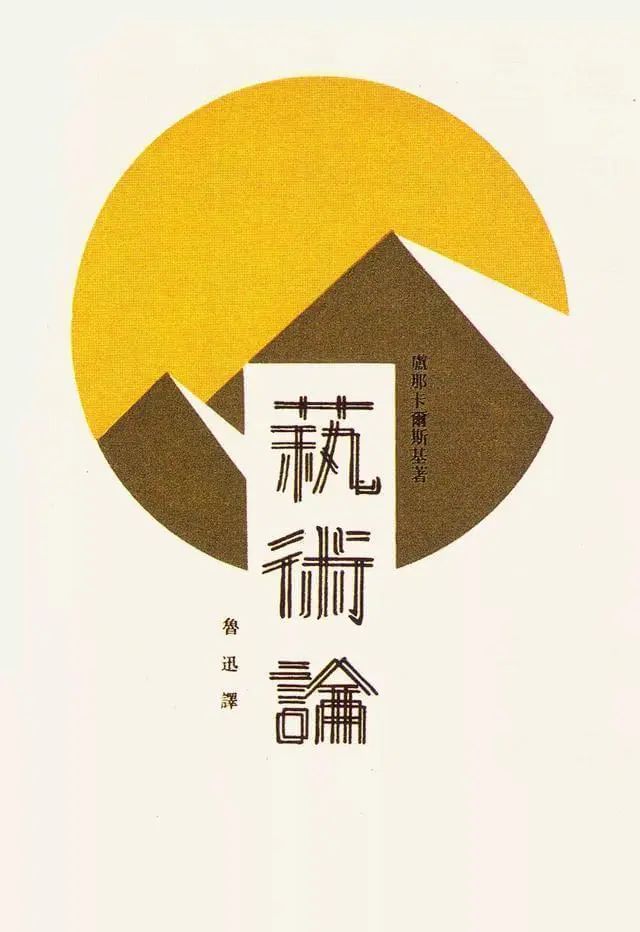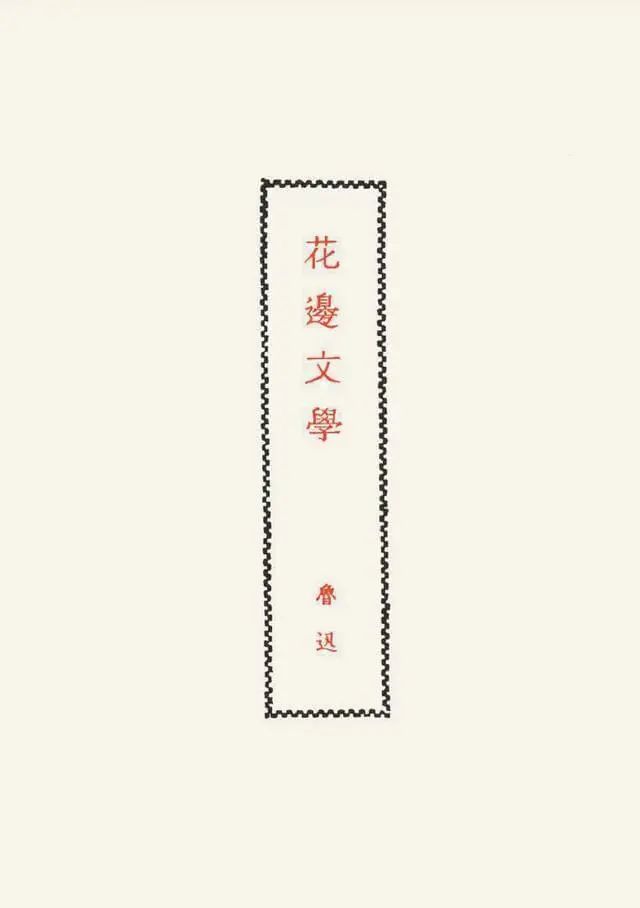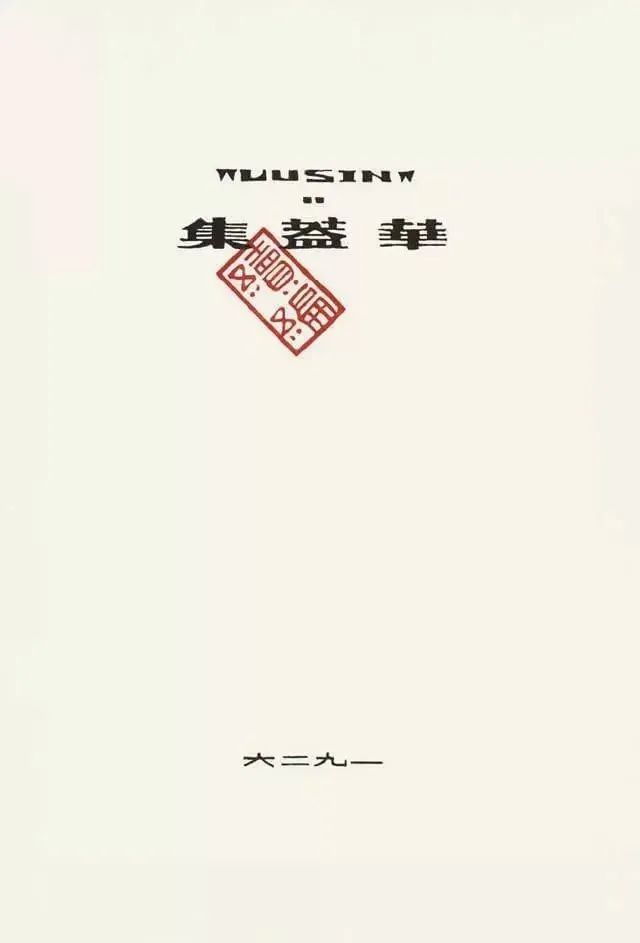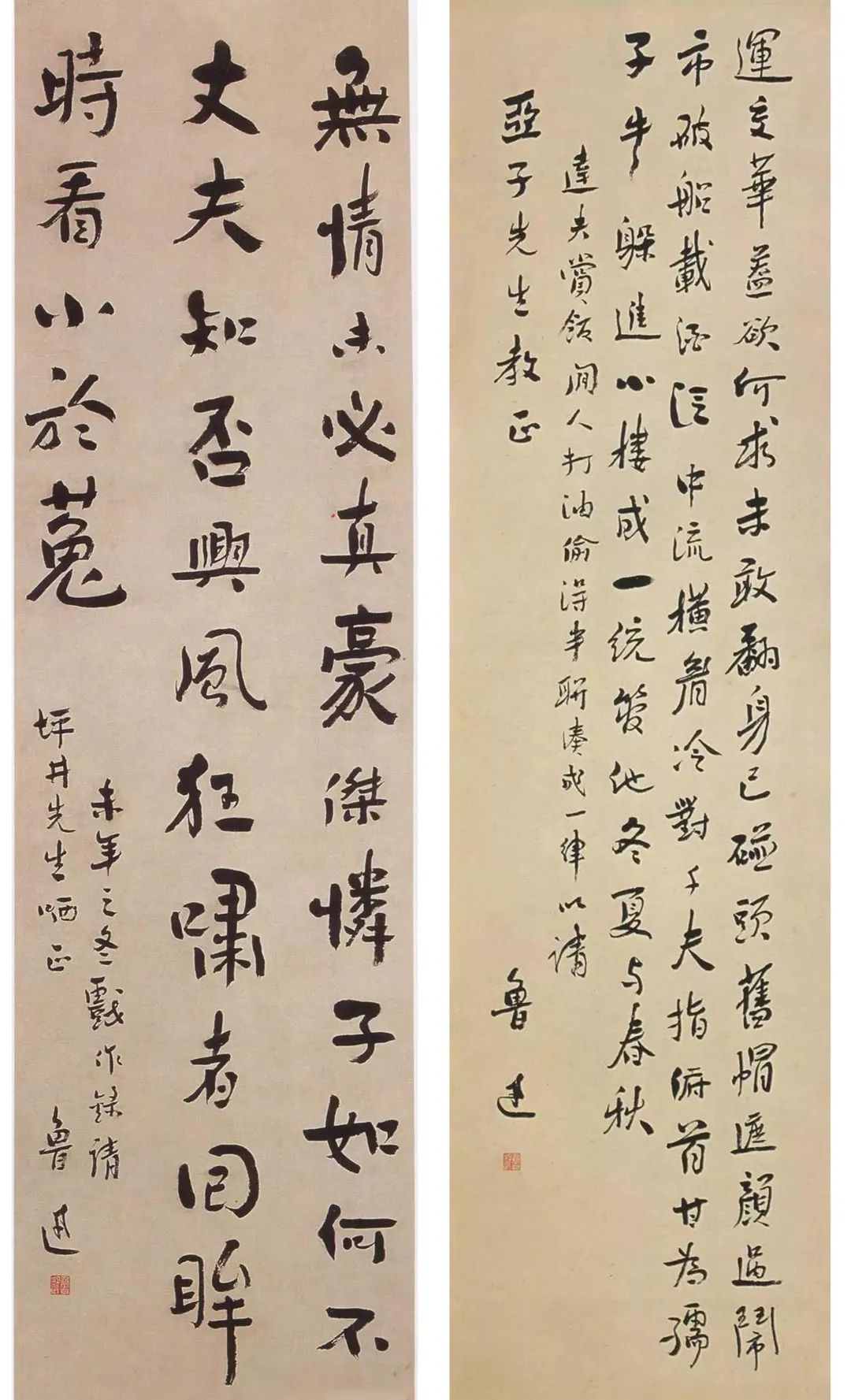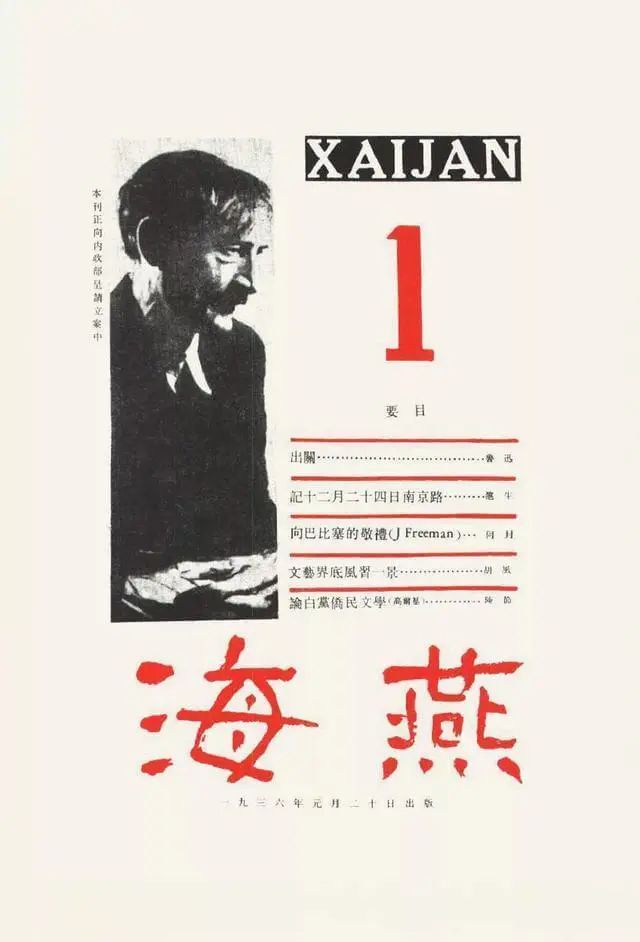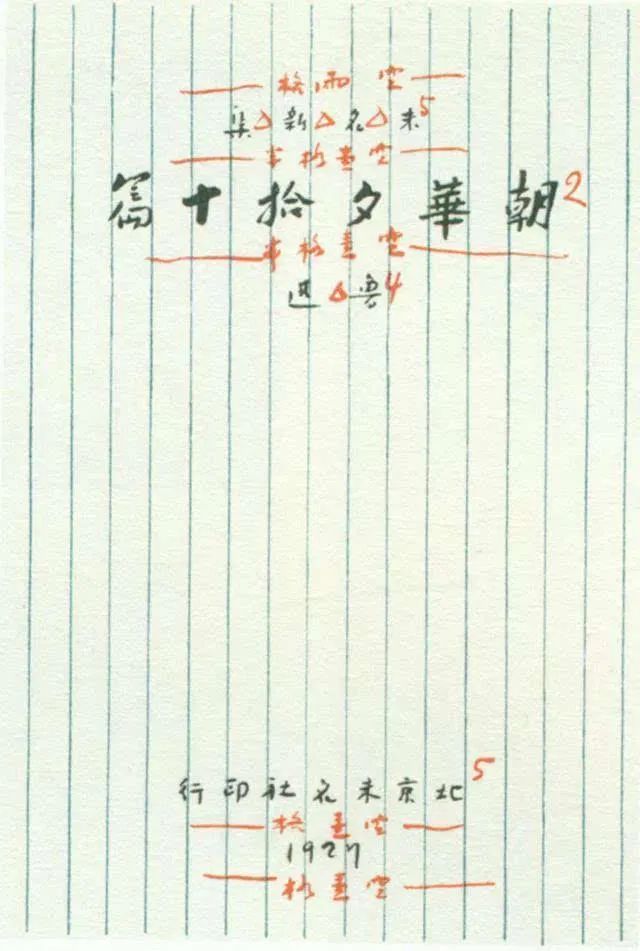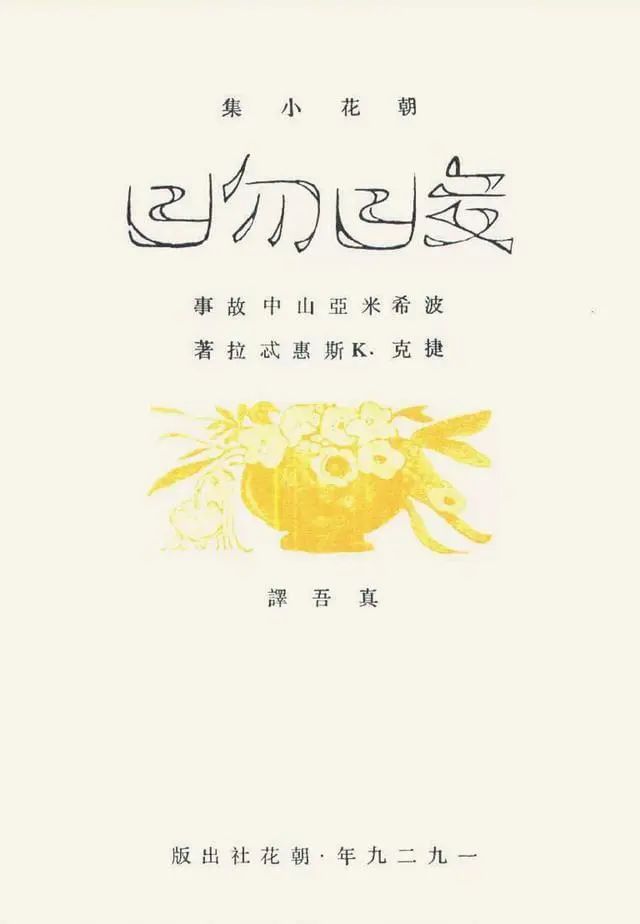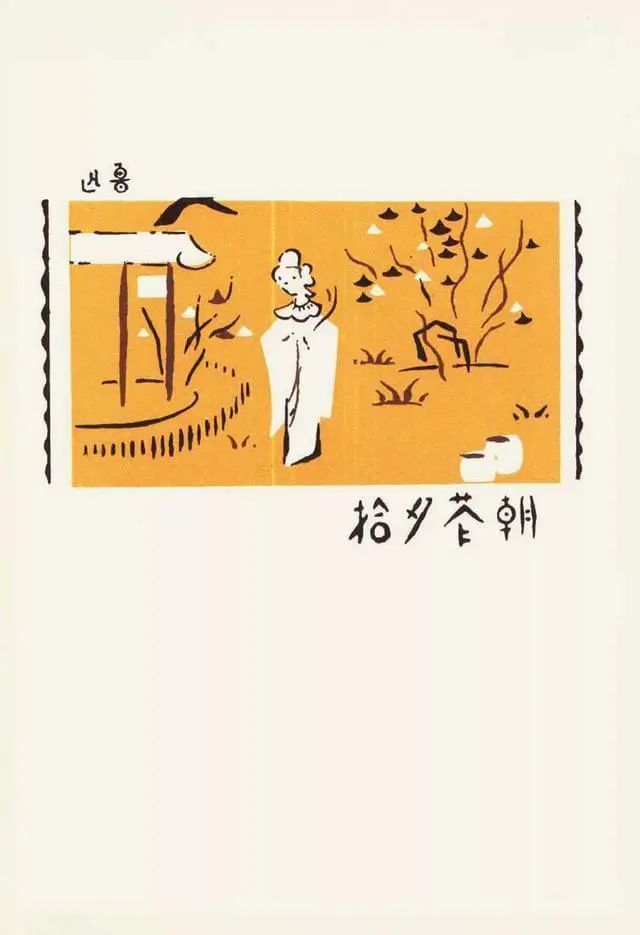
提到鲁迅先生,大家印象最深的是什么?
有的人会说是他的那些金句,有的人会觉得是他那两撇胡子,而我印象最深的就是中学课本里,他那些文学作品,和文章后面的背诵全文,对于鲁迅先生,我们每个人都知道,他是伟大的文学家,思想家,殊不知,鲁迅先生还有不为人知的一面,创作一本书,主笔是他,插画是他,封面设计是他,装帧也是他,样样精通,所以如果只是说他是文学家,那这个定位稍微有些片面了,今天我们就来聊一聊鲁迅先生的那些设计作品。
鲁迅1881年出生在浙江绍兴,爷爷爸爸都是文人,父亲是秀才,但是因为种种原因入狱,出狱之后终日饮酒,导致患病,当时鲁迅也只是十多岁的少年,在三味书屋学习,但是作为长子,他知道自己肩负的责任,那之后他每天都要跑当铺药铺去给父亲抓药,据鲁迅先生后来回忆来看,当时他在当铺受的侮蔑是让他刻骨铭心的,父亲去世之后,他便离开了故乡。
鲁迅先生念过的<三味书屋>他说:“书没读成,画的成绩却不少了,最成片段的是《荡寇志》和《西游记》的绣像,都有一大本。”
在《阿长与山海经》和《从百草园到三味书屋》中都有描述过鲁迅先生儿时非常喜欢带有绘图的书籍,就是在这里,鲁迅先生埋下了艺术的种子。
之后他去了南京江南水师学堂求学,以优异的成绩获得公费赴日本学习的机会,在日本,他读了很多关于美学和文学方面的相关书籍,但他一直抱有学医的梦想,希望学成归来之后能救治像他父亲一样的病人,遇到战争也可以当军医,但是后来因为看了关于同胞被屠杀的照片,这成为了他弃医从文的引子,鲁迅先生开始自学德文和俄文,翻译欧洲弱势国家的文学著作,就这样留学十年归国开始从事文学创作。
南京江南水师学堂
因为文学创作小有名气之后,鲁迅先生把全家都接到了北京,然后在北京八道湾11号买了个院子,这个院子经常高朋满座,一天鲁迅先生的弟弟周作人请来了当时是北大校长的蔡元培,蔡校长当时就向鲁迅发出了去北大任教的邀请,做了任教育部社会教育司第一科科长,这时,他沉迷于收集研究拓本之中,这些工作极大提升鲁迅对美学的理解,并且让他对艺术的兴趣也越发浓厚。
八道湾11号
鲁迅和蔡元培
从鲁迅先生的经历来看,他对美学一直有很浓厚的兴趣,并且在从小到大对于美学研究中也达到了很高的审美水准,所以鲁迅创作的大部分文学书籍,都由他亲自操刀设计,而他最出名的设计应该就是——北大校徽
鲁迅设计的北大校徽
瓦当
鲁迅设计的北大校徽造型是中国传统的瓦当形象,简洁的轮廓给人现代的感觉。“北大”两个篆字上下排列,上部的“北”字是背对背侧立的两个人像,下部的“大”字是一个正面站立的人像,有如一人背负二人,构成了“三人成众”的意象,给人以“北大人肩负着开启民智的重任”的想象。并且它还象脊梁骨,借此希望北京大学毕业生成为国家民主与进步的脊梁。
改后的校徽
鲁迅将校徽图样寄交蔡元培后立即就被采用,一直延续到1949年,后又因历史原因长期弃用,直到上世纪80年代又重新使用。2007年6月,北京大学发布《视觉形象识别系统管理手册》,正式推出修改后的北大校徽标识,这一标识正是在鲁迅设计的校徽图案基础上丰富和发展而来。
书籍设计
很多人称鲁迅是“中国书籍装帧第一人”,我觉得这个称号一点不为过,鲁迅这一生设计的书籍有六十多个,大多是在书籍的字体设计方面,其中也包含一些绘图,印刷工艺方面的设计,并且在那个动荡的时代有很多前卫新潮的思想,为中国书籍装帧设计奠定了良好的基础
1923 年《呐喊》封面设计
其实鲁迅先生对于书籍封面设计,大多数是在字体设计方面,在那个没有PS、AI的年代,这些设计都是靠手绘出来的。
《呐喊》的封面,整体设计就像一个印章一样,古朴、干练,其余画面大面积留白,红色代表血迹,黑色代表斗争,两个颜色形成强烈的对比,“呐喊”两个字被“锁”在黑色的色块里,其实也正印证了他这本小说集的中心思想,就是以大声的呐喊惊起被密闭在“铁屋子”里熟睡而不知死亡将至的民众,呼唤大家齐心合力毁坏这“铁屋子”,以争取新的生命。
1928 年《奔流》月刊封面
《奔流》月刊,鲁迅先生在上海创办并亲自主编的第一份文学刊物,封面的字体也是由鲁迅先生手写设计的,如果放到现代的设计师身上,可能对“奔流”从字义上来设计的话,会设计出比较圆滑、流淌的感觉,而鲁迅先生为什么设计的这么硬朗,横平竖直呢?其实这也要结合当时的社会环境和《奔流》当时刊载的一些文章作为出发点,这个刊物意在介绍一些真正的革命文艺理论和作品,把那些犯幼稚病的青年稍稍纠正一点。所以,可想而知,为什么字体会那么“坚硬”了。
《艺术论》
这是鲁迅先生翻译出版的书籍,采用了现代艺术的简约线条和色块,颇有一些包豪斯的感觉,“艺术论”改造了繁体的「藝」字却完全不影响识别。而文字设计为什么采用双层描线的字体呢?我猜应该是根据书中内容,也就是阐述了对于艺术与其它思想的关系,这两层互融的概念,并且增强了文字的空间感,使文字在醒目的图案下不失气势,同时填补了后方图案的缺口。
1983年《萧伯纳在上海》瞿秋白 【编】 鲁迅封面设计
这个书籍虽然不是鲁迅编写,但是他参与写了序言,而作者是他多年的好友,这本书是辑录了戏剧学、文学家加萧伯纳夫妇访问上海时候一些文章和评论。
书封设计采用的是在当时非常前卫的前贴报纸艺术,鲁迅先生利用上海各家报纸对萧伯纳的头条报道,拼接成了封面的背景,含蓄又自然地介绍了萧伯纳受到的热烈追捧。这种重复的手法会给人很强的视觉印象。
1930年《萌芽》月刊
这个字体设计就很有意思了,字体笔画的粗细变化比较大,一边粗一边尖,“萌芽”上面的尖角,仔细观察形状上都有些差异,就像正在肆意生长的嫩芽一样,没有规矩,却有顽强的生命力。整体来看质朴、简约。“萌芽月刊”四个字占据了封面的大部分空间显得更加醒目。
1934年《花边文学》
这是鲁迅的杂文集,收录了六十一篇杂文。为什么叫花边文学呢?起因是,当时有一些“键盘侠”说鲁迅的文章是“花边文学”,嘲笑他只会写当下社会中的新闻小事,鲁迅就直接“借用”了他们给的“绰号”命名。因为这类短评,在报上登出来的时候往往围绕一圈花边以示重要,所以先生也用花边来呼应主题。
1925年《热风》
这也是一本鲁迅先生的杂文集,收录杂文41篇,当时这些杂文创作背景是处于一个黑暗的时代,而封面的字体则采用一种手写字的形式,懂字体设计的同学可能知道,这种手写感会给人一种人情味和温暖的属性,我猜想鲁迅先生想在那种刺骨的环境下,给人以「热风」一般的暖流。
1926年《华盖集》
这个也是一本杂文集,收录了鲁迅创作的三十一篇杂文。发现没有,鲁迅先生大多数的封面都是很朴素的,除了书名和作者,再看不到其他设计。
从《热风》的手写体到《华盖集》的印刷体美术字,都可以看出鲁迅先生对字体的独特见解。
1932年《南腔北调集》
这也是一本杂文集,这个书名也是来自于攻击他的人,说他的演讲是南腔北调,鲁迅先生就调皮的使用了这个名字,表明了自己不愿随波逐流,鄙薄无聊文人的立场,信手拈来的这个名字,诙谐幽默之中,也表明了对敌人的鄙视,将它命名为《南腔北调集》,是一种自嘲,更是对对方的嘲讽。
再来看封面设计,同样手写字的封面设计,这个手写感和《热风》就不同了,这个感觉文字更松弛一些,说到这,不得不提一下鲁迅先生的书法了
鲁迅先生真的是全能,他在书法上也颇有造诣。源于早年抄写过很长时间的古碑,并热衷于搜寻碑帖拓片,对书法、美术有着很高的鉴赏力。他的书法,古雅厚重,文人气十足。所以他的书籍封面常由他自己设计。
1923年《歌谣纪念增刊》
这本书收录了很多歌谣和关于歌谣的论文,虽然作者不是鲁迅,但是封面是他设计的,底色为深蓝色,表示月夜。几缕淡淡的闲云,一钩斜月。左上角是沈尹默的手迹,写的是一首儿歌《月亮光光》。右下角是鲁迅的笔迹:“歌谣纪念增刊北大二十五周年研究所国学门歌谣研究会出版”。其实这不就是典型的对角线构图嘛,整个画面给人一种幽雅、静谧的气质。
1929年《小彼得》
这本是一本童话书,是鲁迅先生和他的爱人许广平一起翻译的,“小彼得”的字体设计也充满了童趣。
1936年《海燕》第一期
在 1936年 1 月 20 日,《海燕》第一期面世,整个封面设计和之前不一样了,是图文的搭配,一下就能看出鲁迅先生功力深厚,设计的目的就是美观快速的传递信息,他在这个封面上就兼顾了很多设计规则,比如两端对齐,为了避免出现太多留白和字号过大,先生的处理方式是用虚线链接,用红线分割,稳中有序,封面上红色的手写体 "海燕" 特别显眼。并且上线当日即告售罄,鲁迅在日记中专门记载此事,尤为兴奋。
1922年《桃色的云》
这是诗人爱罗先珂作的童话剧,通过孩子烂漫幻想反映了社会问题,是一部成人和孩子都可以读的童话书。
看到这个封面设计,你是否会有疑问,中国的祥云对应主题,觉得不像一个童话剧。其实这也是鲁迅先生给大家埋的伏笔,为的就是激起读者的好奇心。
鲁迅先生一些手稿
鲁迅先生在印刷时细致的标注了空行和空格的位置,对于字号大小,可见先生在设计时有自己的一套理论思路的。
鲁迅其他书籍设计作品
向左滑动查看更多作品
鲁迅非常热衷于收藏,不只是收藏书籍,还收藏很多艺术作品,版画就是他的热爱之一,据说鲁迅收藏的版画多达2100多幅,囊括了德国、比利时、英国及日本等名家佳作,被称为“版画界的收藏第一人”,对中国版画界发展起着至关重要的作用。
鲁迅先生还创办过木刻讲习班,培养了李桦、刘岘、黄新波、彦涵、力群、古元等一批优秀的青年木刻版画家和木刻插图家。他们以封面设计和插图创作为主,产生了许多优秀的作品,出现了一个空前繁荣的时期。
鲁迅先生收藏的版画作品
可以看出鲁迅先生收集的版画作品大多是反应人民生活状态的,这也和鲁迅先生的意识形态有很大关系。
鲁迅先生多有钱?
《鲁迅日记》里记录了他差不多三年的收入和支出的账,他一共挣了12万大洋,这个钱在当时是什么概念呢?普通人平均一个月大概能挣十六七块钱,鲁迅先生一个月是挣两三百块钱,当时蔡元培聘请他做教育部的佥事,做佥事一个月工资就是两百多大洋,后来又聘请他做大学院的院士,在大学院鲁迅先生总共挣了一万五千多大洋,他在北京最大一笔开销就是买了八道湾的大宅子,也是我们开篇提到的,但是他大部分资产都用来购买收藏版画作品还有金石篆刻等艺术品了。(ps:部分取自《晓说》感兴趣的同学可以去看看)
《鲁迅日记》手账
任命状
俗话说“不想当医生的作家不是好设计师”,鲁迅先生无论在文学上还是美学上都有很高的造诣,只不过文学锋芒太显眼,设计师的身份反而被掩盖了,但不得不说,在那个动荡的时期,鲁迅先生对于中国艺术的发展做出了很多贡献。现如今人们愿意神话鲁迅先生,甚至会拿一些非鲁迅先生所言的句子去作为自己攻击被别人的“武器”,在此用鲁迅先生说过的话来警醒大家:「现在的青年最要紧的是“行”,不是“言”。」最后,如果大家对于鲁迅先生作品感兴趣的话,可以去买个鲁迅全集了解一下。